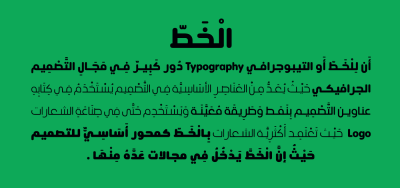
قلم شاد دجلی تاچکیلی
قلم شاد دجلی تاچکیلی (دجادلي تاتشكيلي) یک قلم بسیار زیبای شاد می باشد که در دو نسخه پر و تو خالی منتشر شده است.
قلم زیبای قلم شاد دجلی تاچکیلی منتشر شده است.